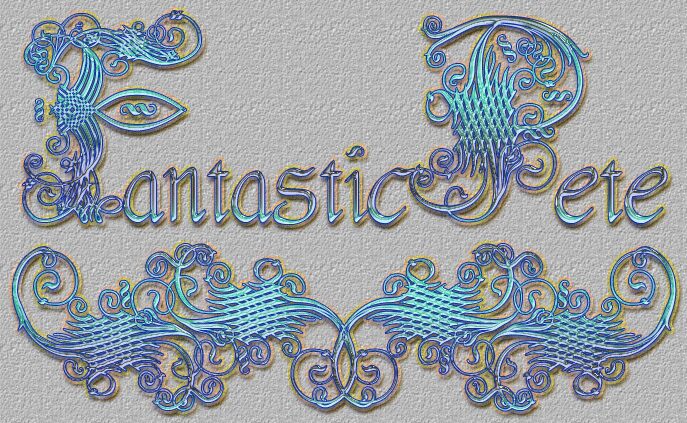
Fantastic Pete od The Mighty Pete to bezpłatny, ozdobny font z gotyckimi inicjałami, który przywodzi na myśl baśniowe ilustracje. Jego znakiem rozpoznawczym są bogato zdobione pierwsze litery: sploty przypominające pnącza, liściaste motywy i delikatne równoległe kreski zamieniają pierwszy znak w dekoracyjną ramę, podczas gdy reszta napisu pozostaje lekka i płynna.
Ten darmowy font doskonale sprawdzi się na okładkach książek, w papeterii ślubnej, dyplomach, plakatach oraz na początkach rozdziałów, gdzie jedna misterna inicjał nadaje ton całej kompozycji. Pasuje również do monogramów i krótkich nagłówków, zwłaszcza gdy chcesz, aby pierwsza litera odgrywała główną, teatralną rolę i wprowadzała romantyczny, starodawny klimat.